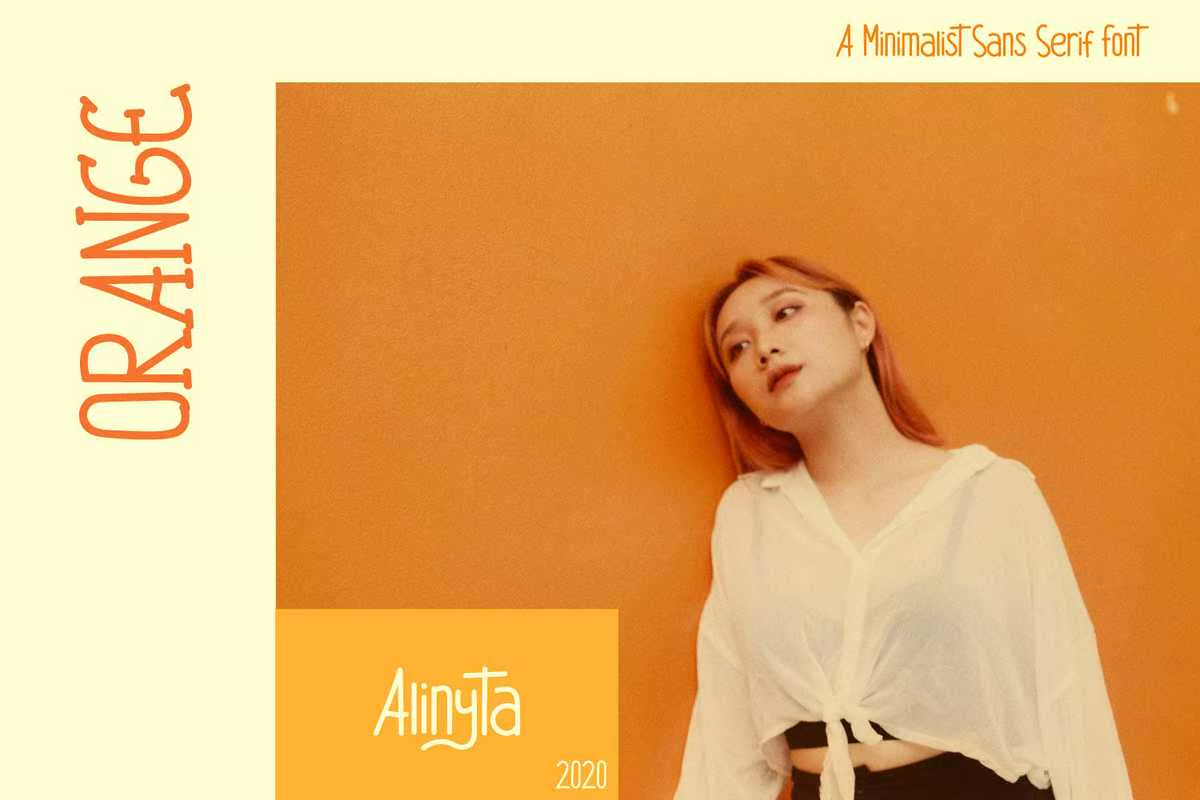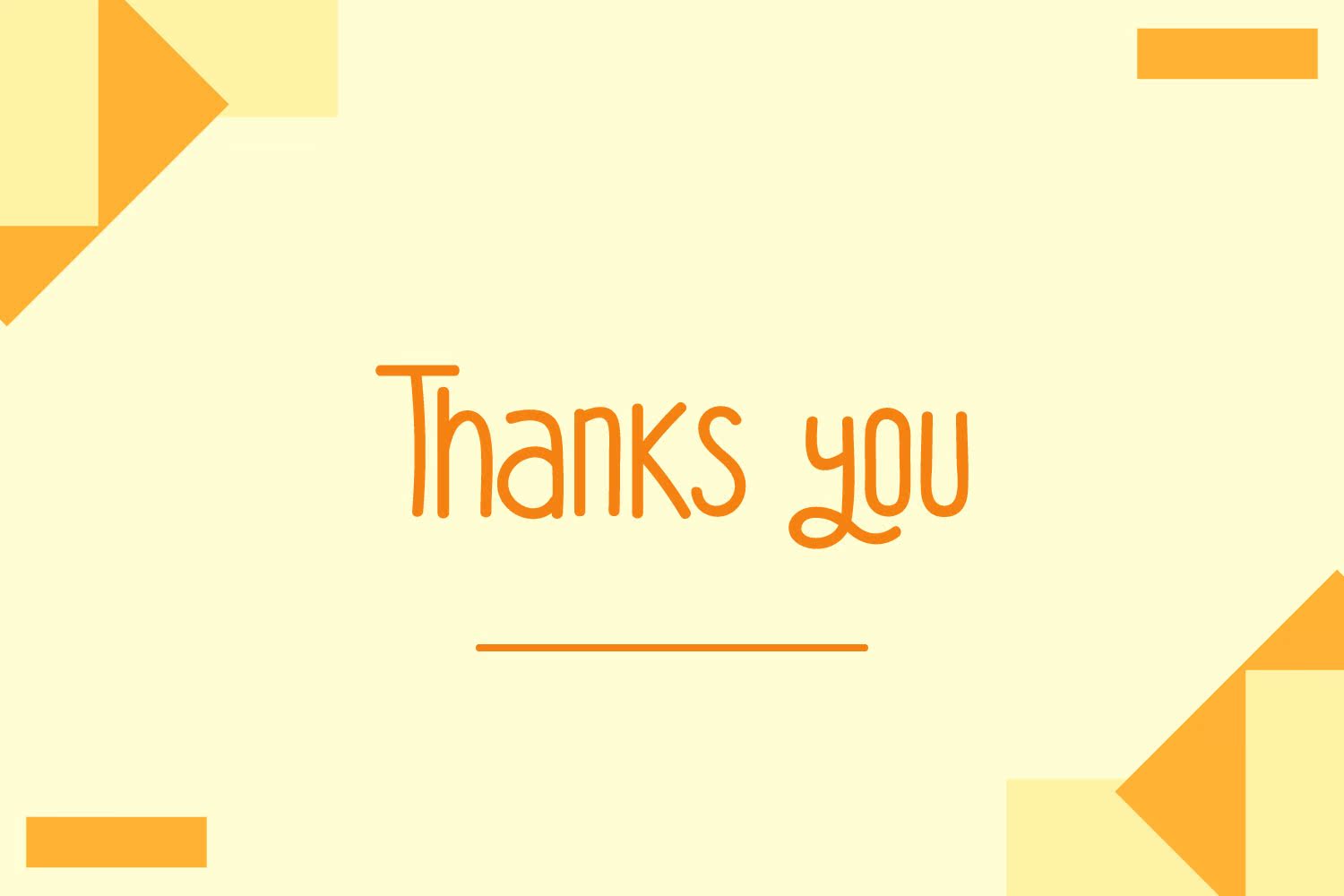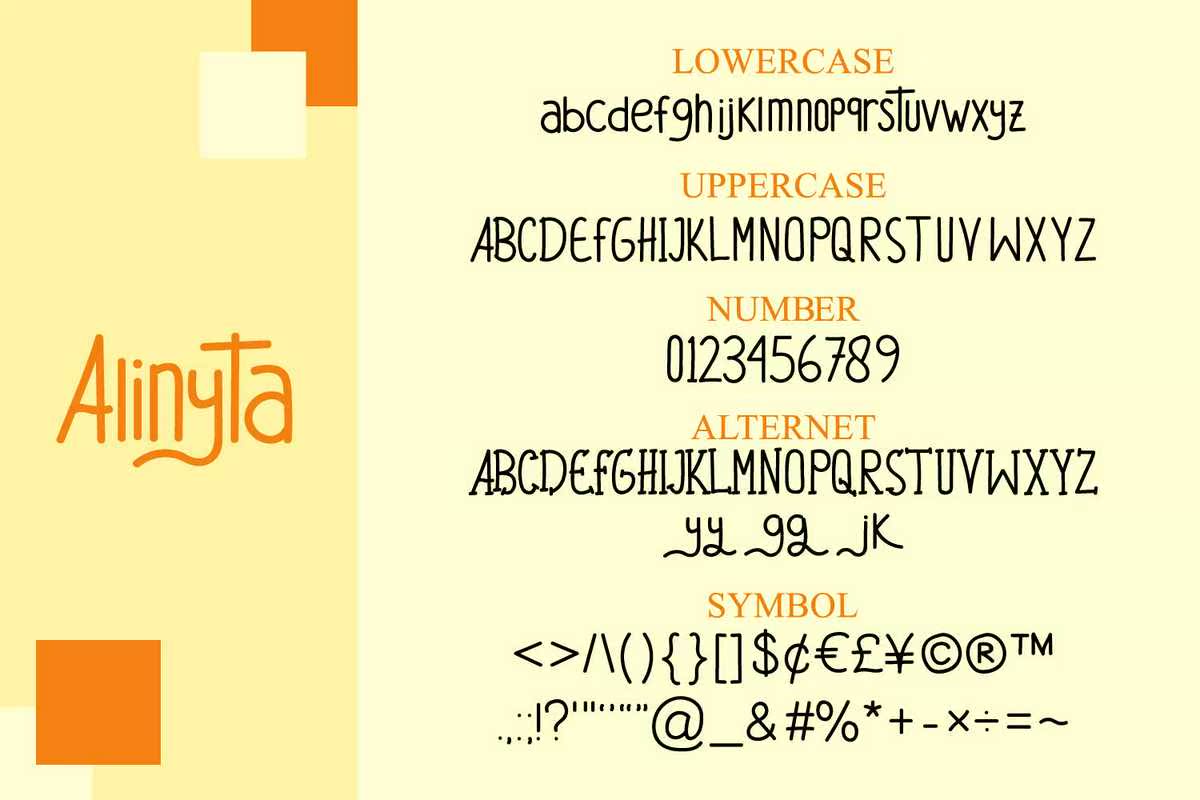
AlinyTainima是一款吸引眼球的书写字体,同时具有两个签名和验证字符。它适用于您希望开发的任何品牌、产品包装、邀请、报价、t恤、标签、海报、徽标。此字体经过编码,意味着您可以访问可用的图示符和SWASE!AlinyTainima是一款吸引眼球的书写字体,同时具有两个签名和验证字符。它适用于您希望开发的任何品牌、产品包装、邀请、报价、t恤、标签、海报、徽标。此字体经过编码,意味着您可以访问可用的图示符和SWASE!